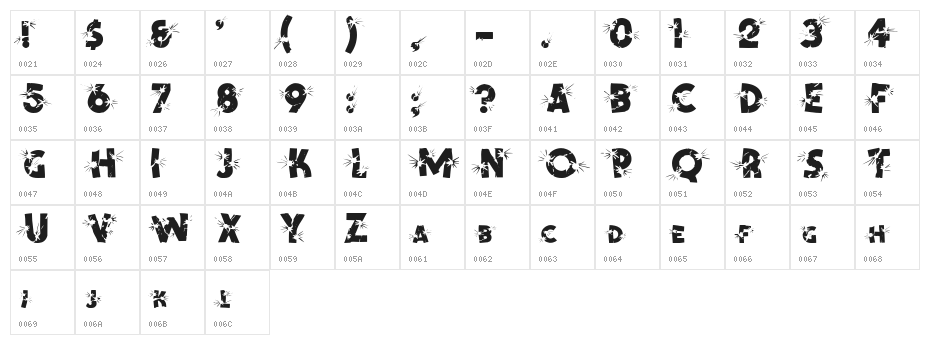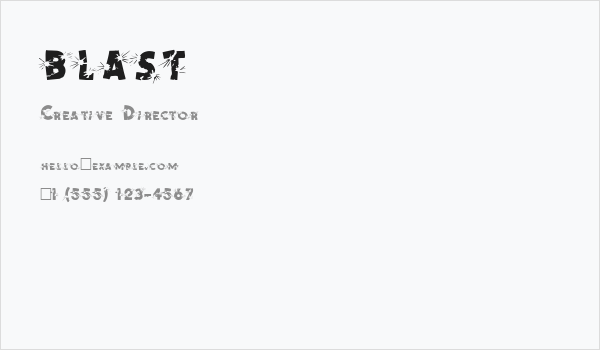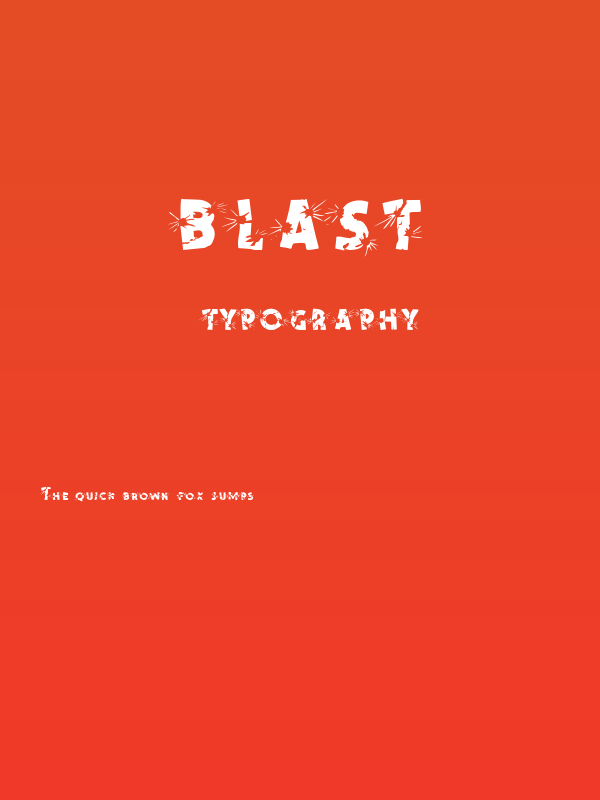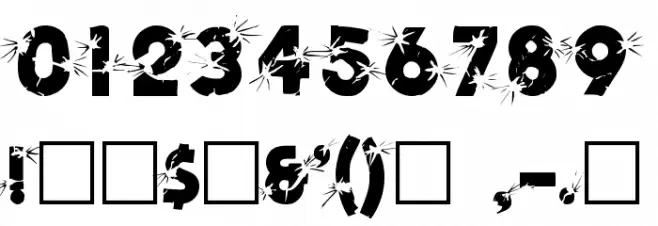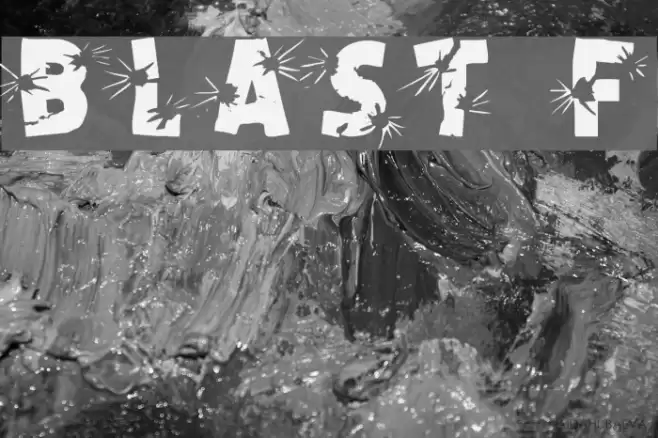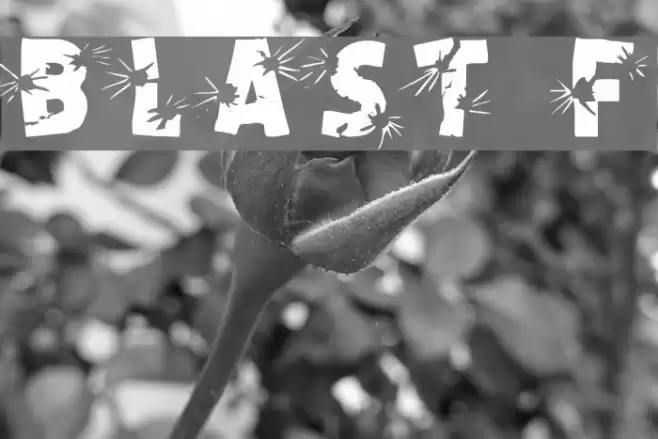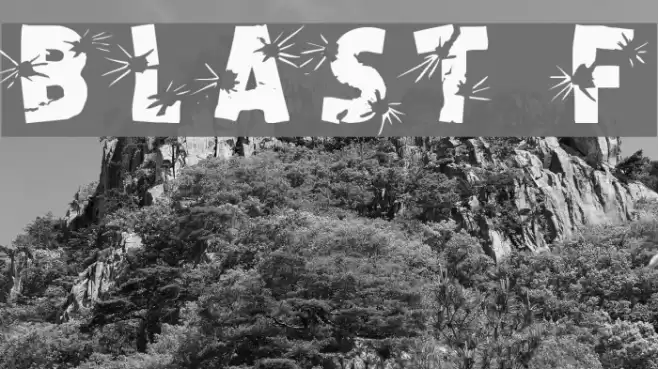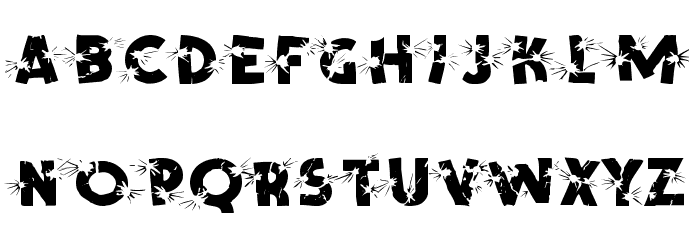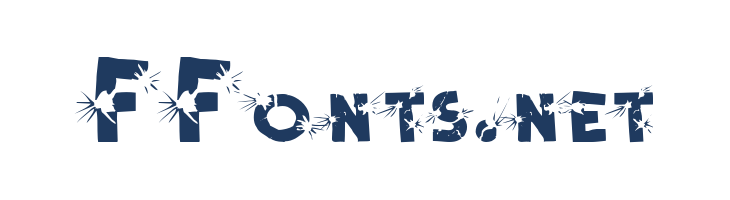
BLAST Font
| Estilo geral | Modern, Edgy |
| Projetos propostos | Ideal for posters, event flyers, video game titles, and any design needing a dramatic and energetic typeface. |